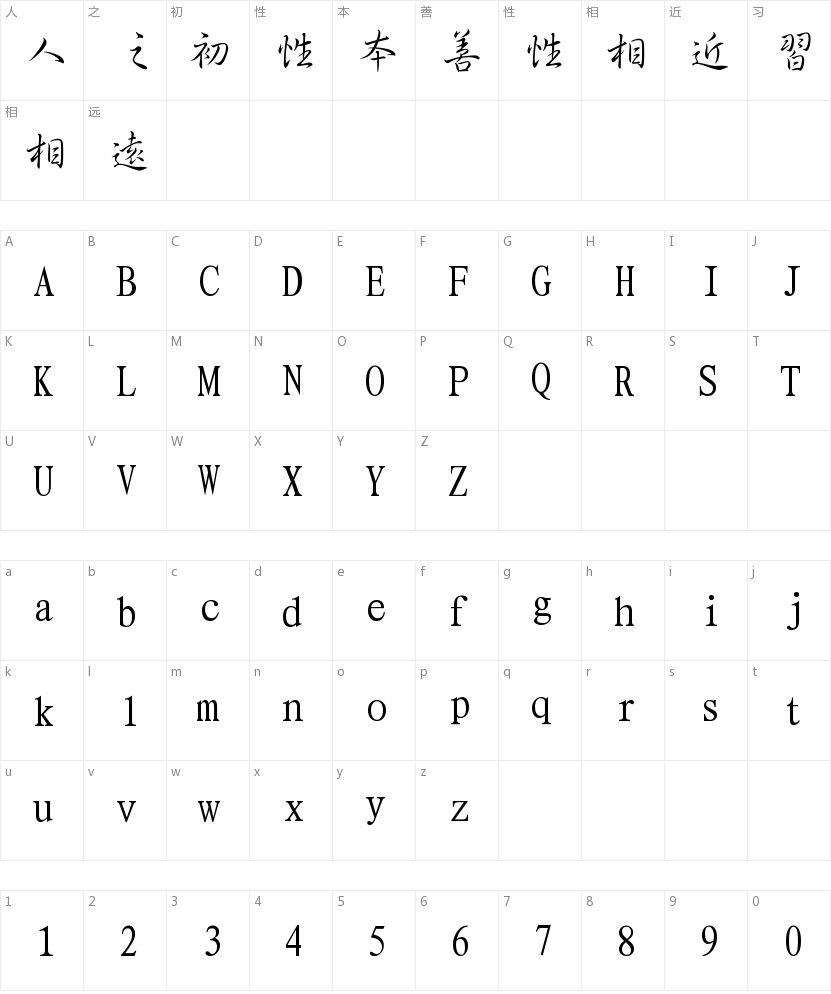
经典繁行书
经典繁行书 字体是一种中国传统的字体,它以楷书为基础,经过多年发展和演变而成。它的特点是字体稳定,笔画流畅,笔划清晰,结构规整,字形丰满,有较强的视觉冲击力。经典繁行书字体在中国文字书写中占有很重要的地位,它的出现使中国书写更加精致,更加优雅。
经典繁行书是一款非常不错的手写艺术字体,具有很好的视觉感,适合于文化类的宣传设计、商业类品牌的广告和产品包装设计以及个性化文字排版等较多场景。